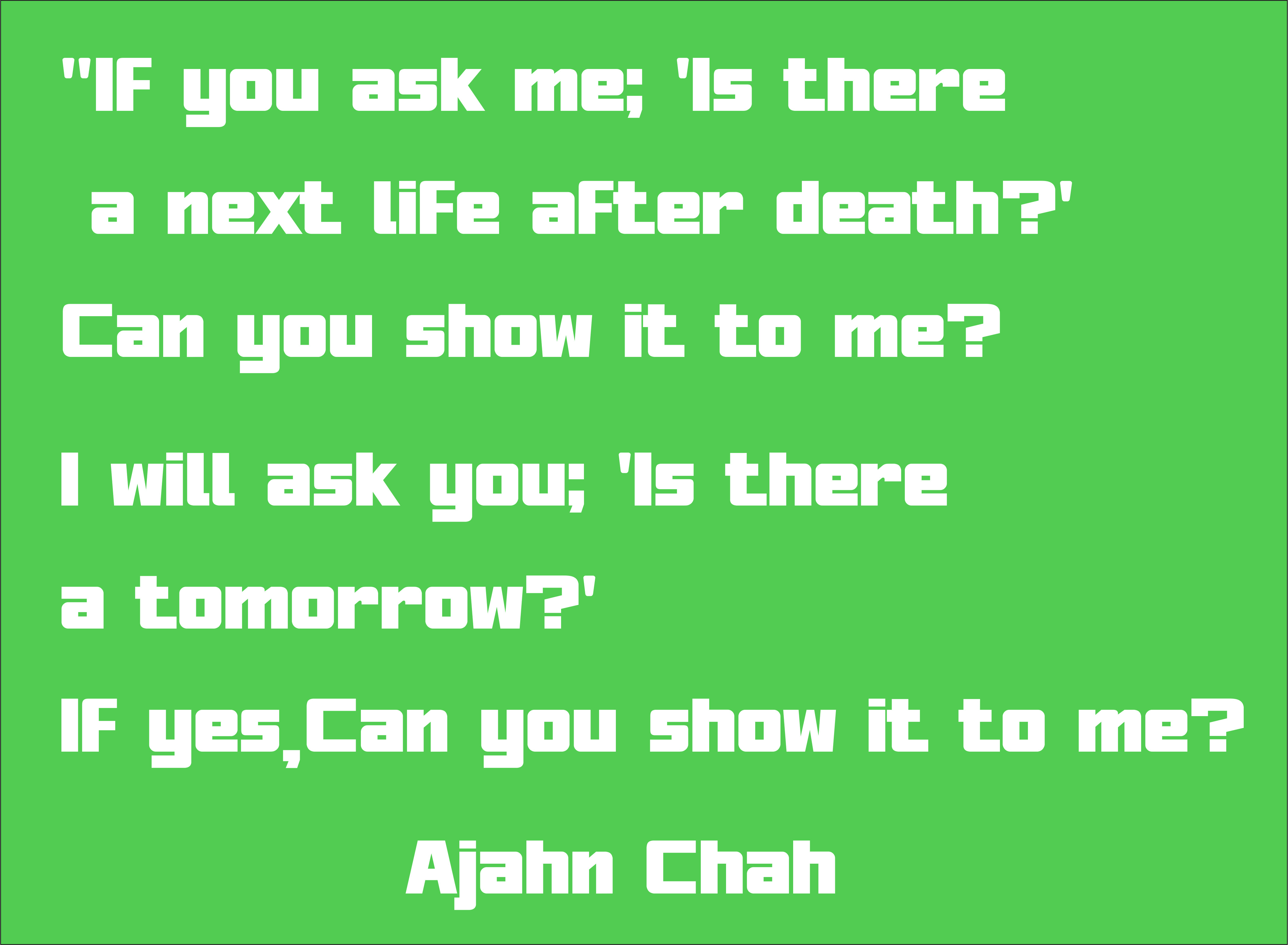
เอสดีนิวนอร์มอล
เอสดีนิวนอร์มอล เป็นฟอนต์ที่ทำไว้ในช่วง โควิท-19 ระบาดรอบแรก ช่วงนั้นปิดร้านไปหลายวันเลยนั่งทำฟอนต์นี้ขึ้นมา
เป็นฟอนต์แนวทางการอ่านง่ายๆๆ สบายตา เหมาะสำหรับทำป้ายบ่งบอกสถานที่ต่างๆ ฟอนต์นี้มีทั้งหมด 2 ไฟล์ .ttf กับ .otf